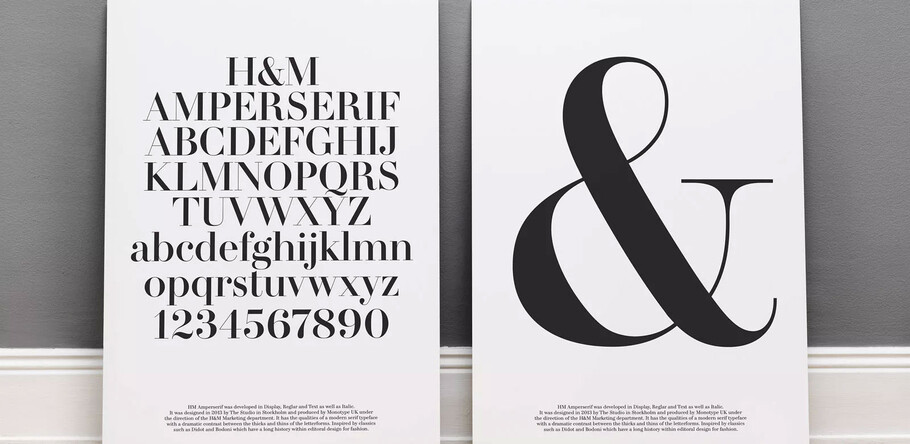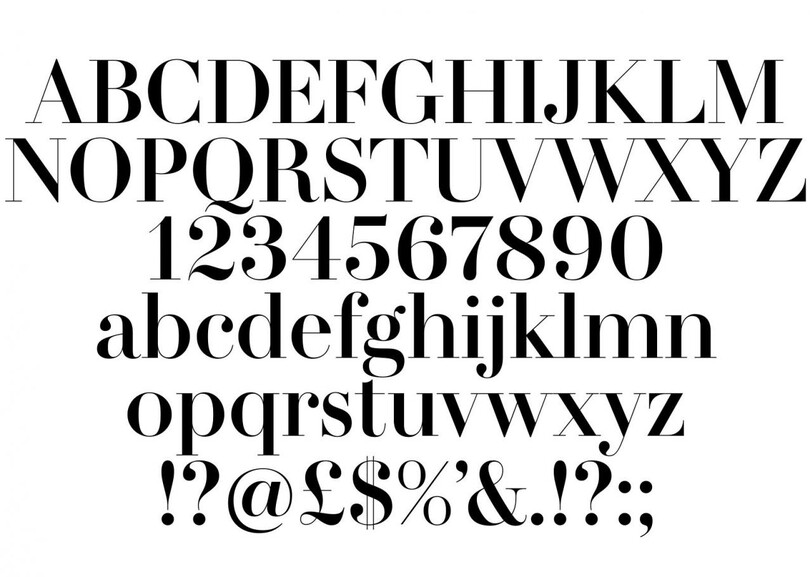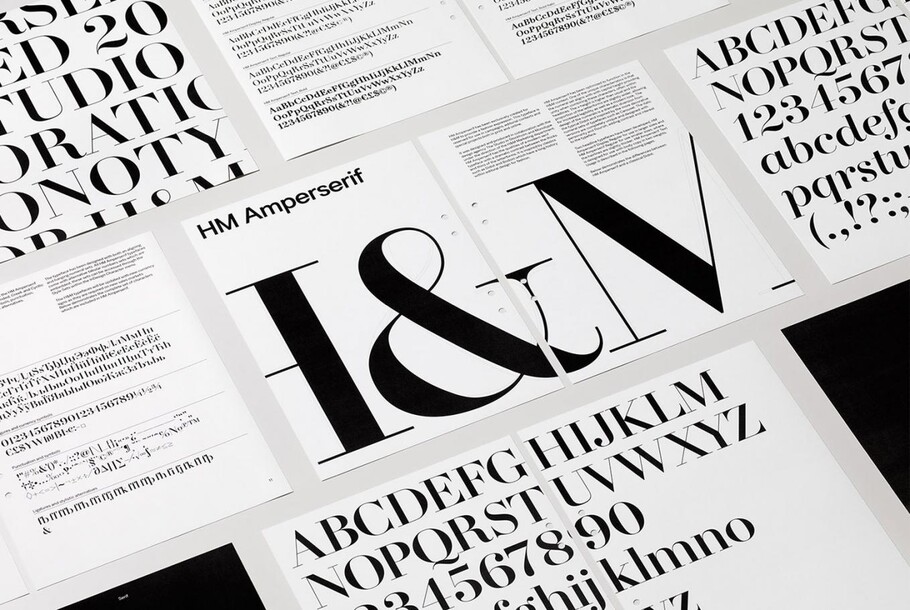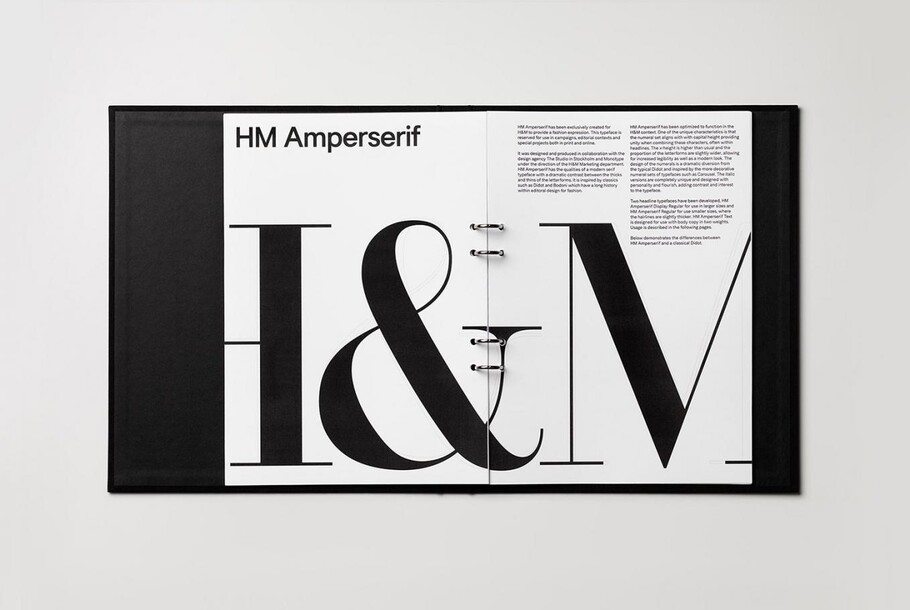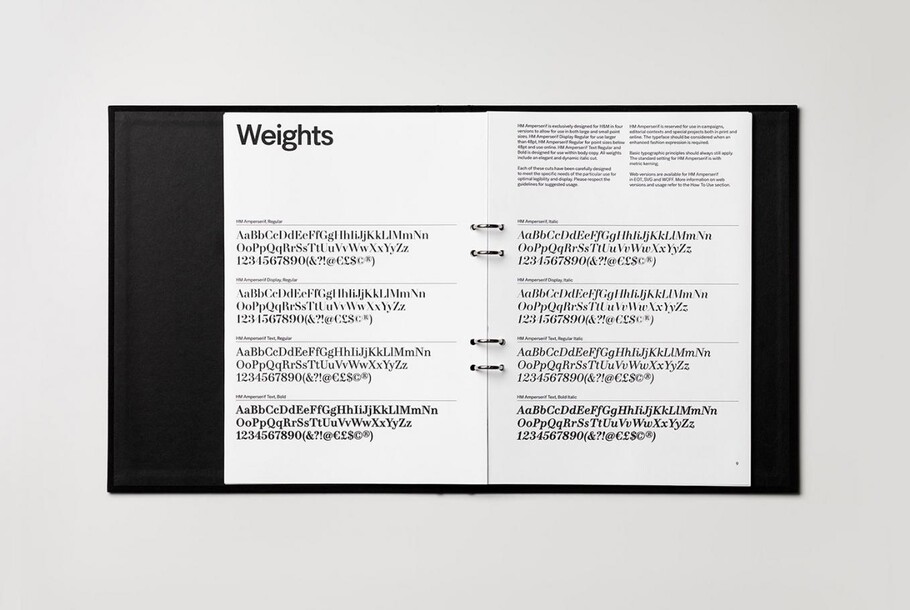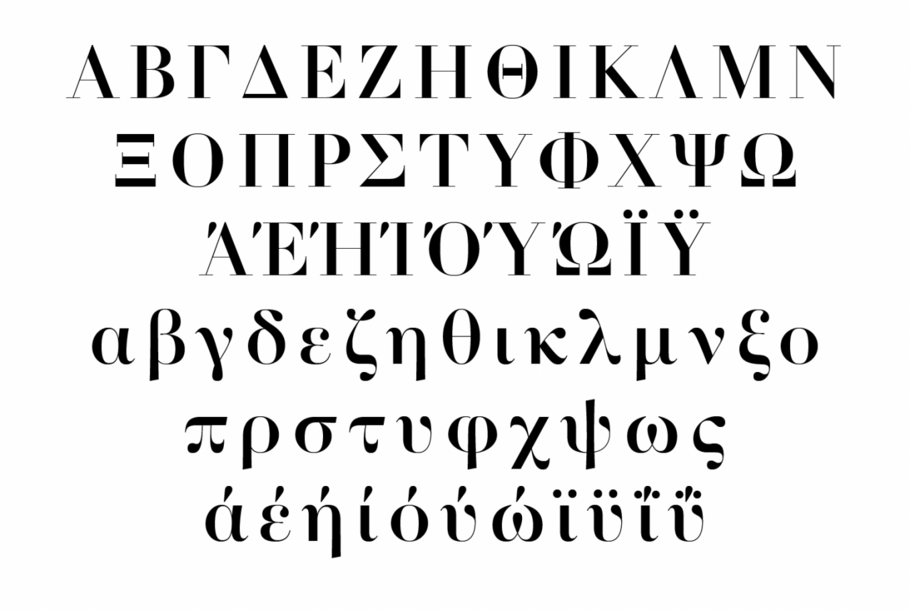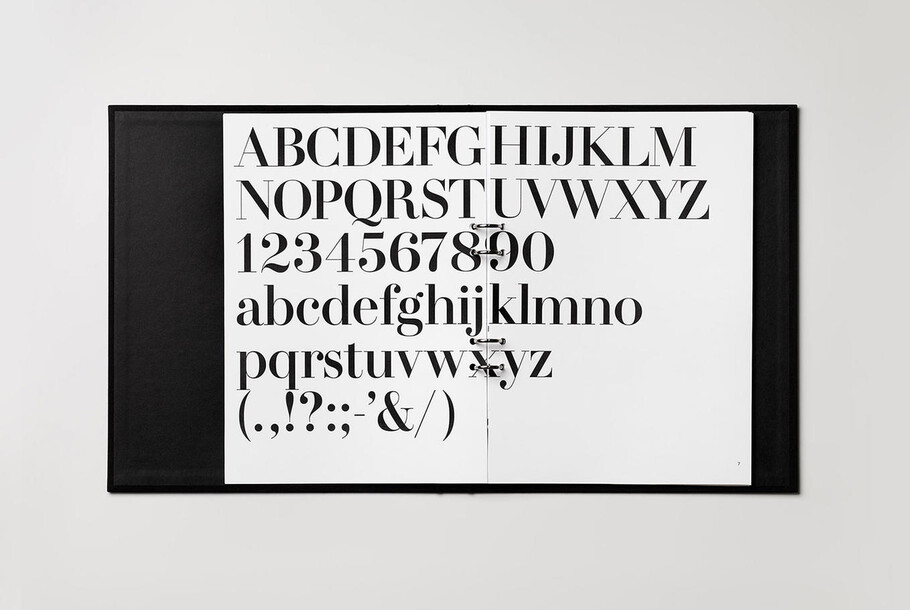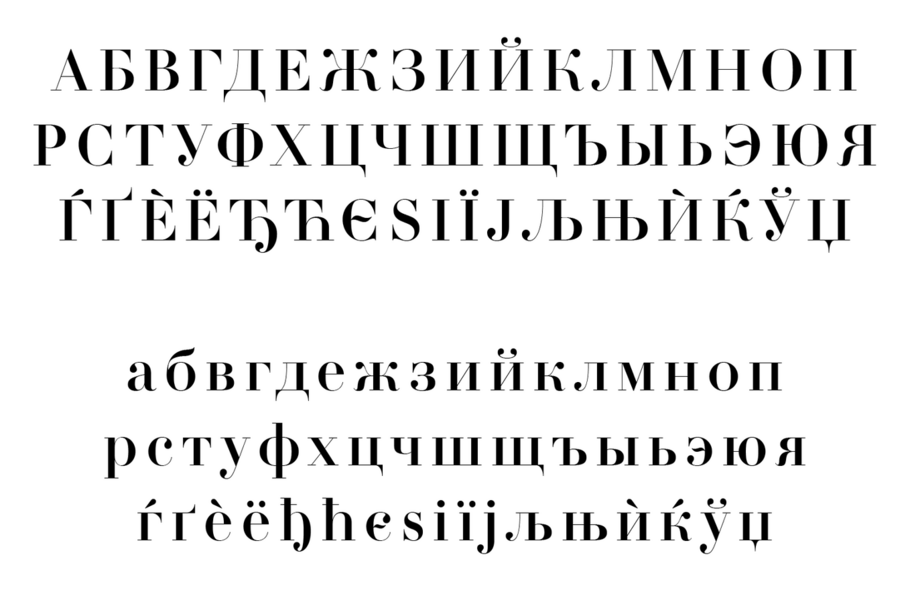
Fashion-Fonts für H&M.
H &M benötigte eine individuelle Schriftart, die bei jeder Kommunikation gut aussieht – von großformatigen Grafiken in den Läden bis hin zu kleineren Schriftarten für die Website und saisonale Lookbooks. Monotype und The Studio arbeiteten bei Design und Entwicklung der exklusiven Schriftart HM Amperserif für die Marke zusammen.
Die schwedische Bekleidungsmarke H&M, der zweitgrößte globale Bekleidungskonzern, betreibt mehr als 3.000 Geschäfte in 61 Ländern weltweit. Die markenspezifischen Inhalte reichen von Werbung und Katalogen bis hin zu Verpackung, Folien und Beschilderung. Obwohl H&M bereits mit dem maßgefertigten Sans-Serif-Font HM Ampersand arbeitete, der ebenfalls von Monotype entwickelt wurde, wünschte sich das Unternehmen eine umfassendere typografische Sprache, die in unterschiedlichem Kontext in aller Welt zum Einsatz kommen konnte. Die Marke beauftragte Monotype mit der Entwicklung einer begleitenden Serifen-Schrift als Kontrast und Ergänzung zum bestehenden HM Ampersand-Design.
Diese zweite Schriftart sollte für Autorität und Stil in jeglicher Kommunikation von H&M sorgen – in großformatigen Grafiken in den Geschäften ebenso wie in kleineren saisonalen Lookbooks. Der Monotype Type Designer Toshi Omagari arbeitete bei der Entwicklung der Schrift HM Amperserif eng mit der schwedischen Designagentur The Studio sowie dem Marketing-Team von H&M zusammen. Dieses Design weist eine ähnliche Struktur auf wie die HM Ampersand, erlaubt H&M aber mehr typografische Flexibilität. Die Marke benötigte eine klare, globale visuelle Sprache, musste aber gleichzeitig ihre Identität wahren und ein breites Publikum ansprechen, alles ohne Abstriche bei der Designqualität..
HM Amperserif greift die langjährige Tradition kontrastreicher Serifen-Schriften auf, die in der Modewelt große Beliebtheit erlangten, nachdem sie in den 1950er Jahren von Magazinen wie Vogue und Elle intensiv eingesetzt worden waren. Die Schriftart setzt diese visuelle Tradition fort, nutzt jedoch auffallende, aber dezente Eigenheiten, wie etwa eine sich leicht verjüngende Strichführung für die untere Schleife des kleinen „g“.
HM Amperserif wurde in drei Größen entwickelt. So wurde sichergestellt, dass ihr Charakter auch bei den größten und kleinsten Proportionen gut zur Geltung kommt – sei es auf Plakatwänden oder auf Einkaufstüten. Gemeinsam mit The Studio investierte Monotype auch viel Mühe in die Gestaltung der Zahlen, um diese für Preisangaben sowie wie für Überschriften von Kampagnen zu optimieren, die bei H&M eine wichtige Rolle spielen
HM Amperserif greift die langjährige Tradition kontrastreicher Serifen-Schriften auf, die in der Modewelt große Beliebtheit erlangten, nachdem sie in den 1950er Jahren von Magazinen wie Vogue und Elle intensiv eingesetzt worden waren. Die Schriftart setzt diese visuelle Tradition fort, nutzt jedoch auffallende, aber dezente Eigenheiten, wie etwa eine sich leicht verjüngende Strichführung für die untere Schleife des kleinen „g“.
HM Amperserif wurde in drei Größen entwickelt. So wurde sichergestellt, dass ihr Charakter auch bei den größten und kleinsten Proportionen gut zur Geltung kommt – sei es auf Plakatwänden oder auf Einkaufstüten. Gemeinsam mit The Studio investierte Monotype auch viel Mühe in die Gestaltung der Zahlen, um diese für Preisangaben sowie wie für Überschriften von Kampagnen zu optimieren, die bei H&M eine wichtige Rolle spielen